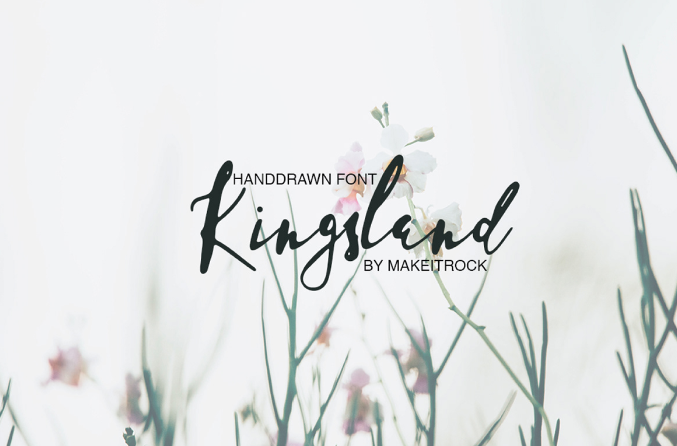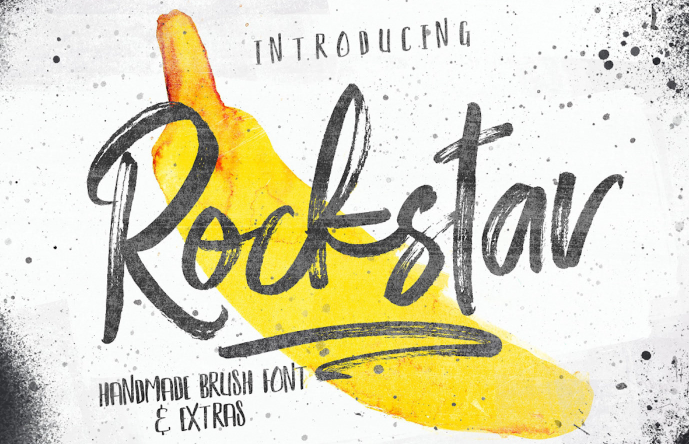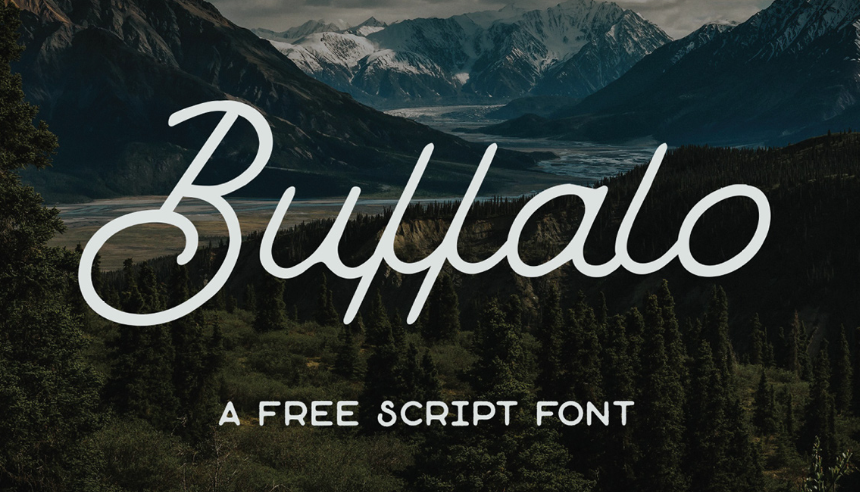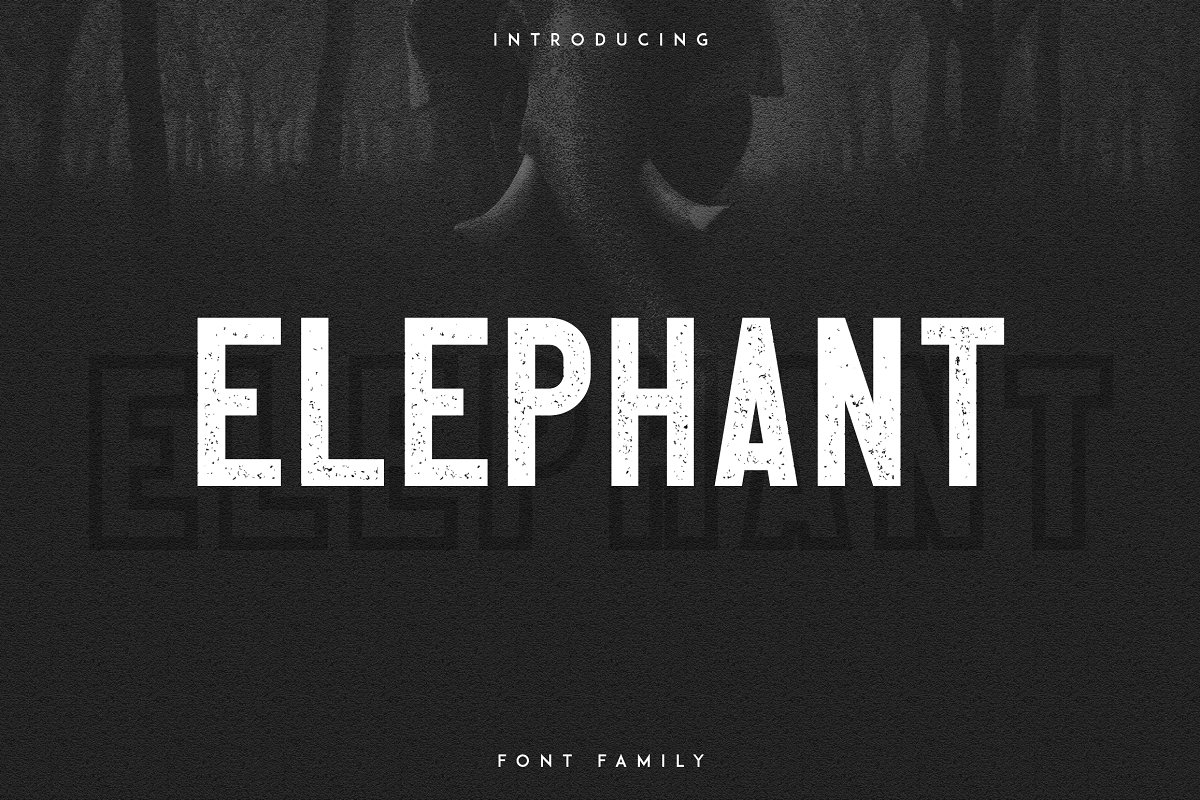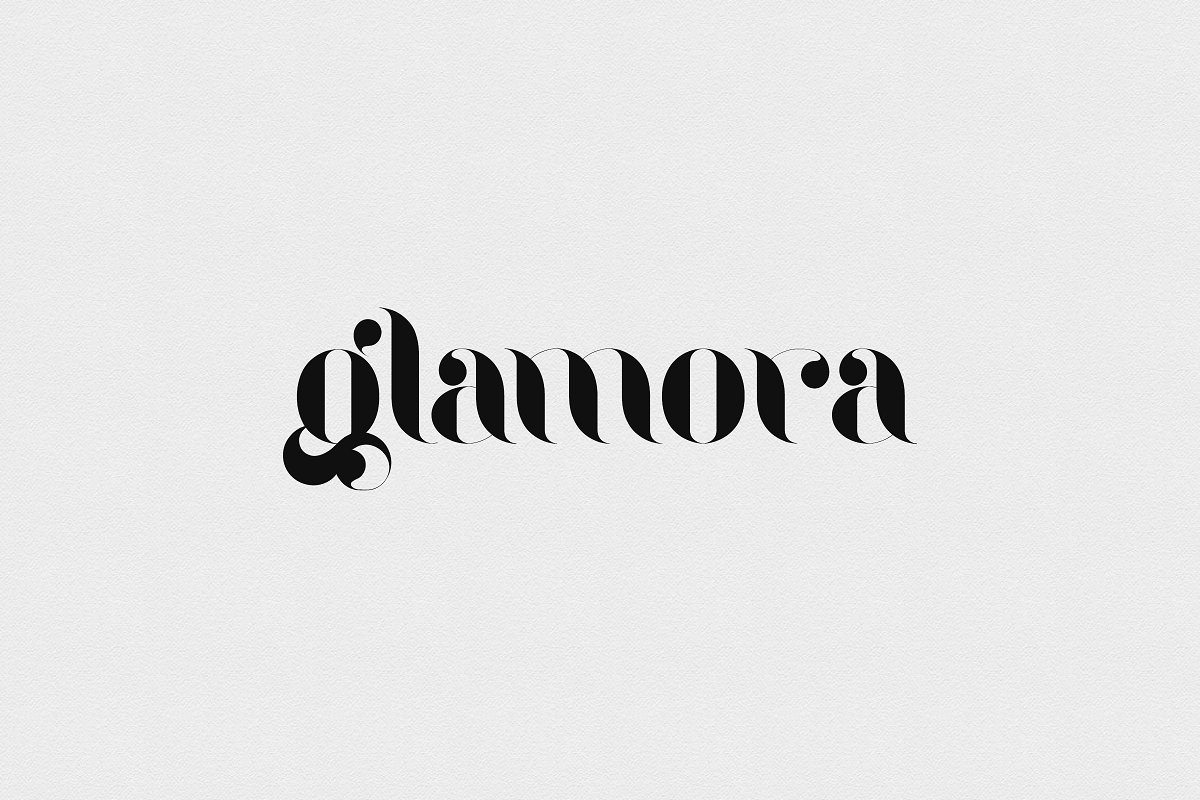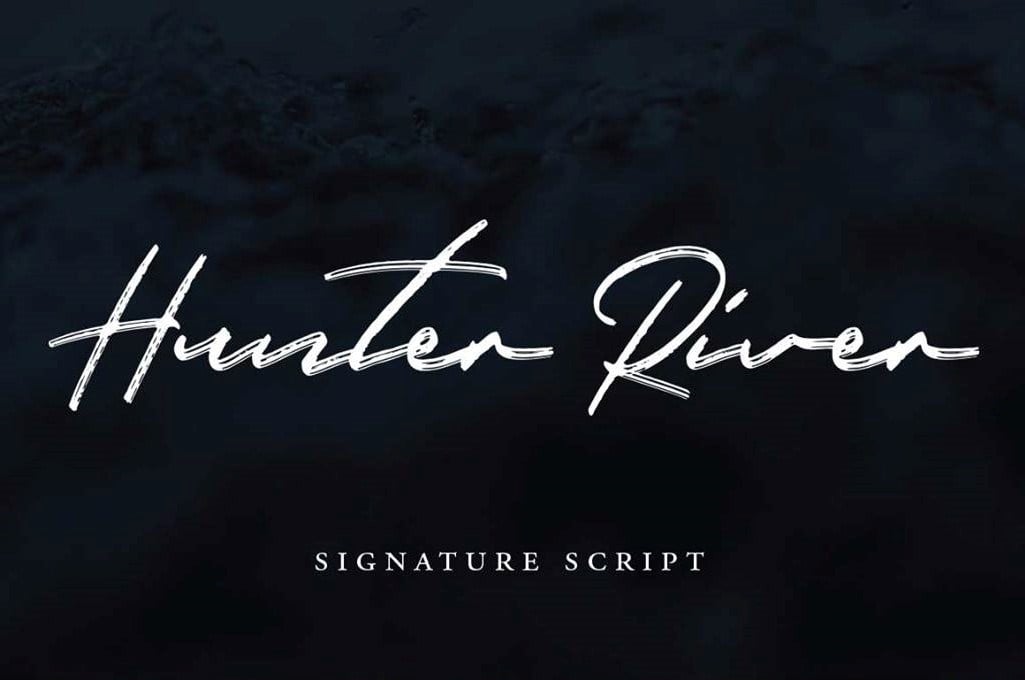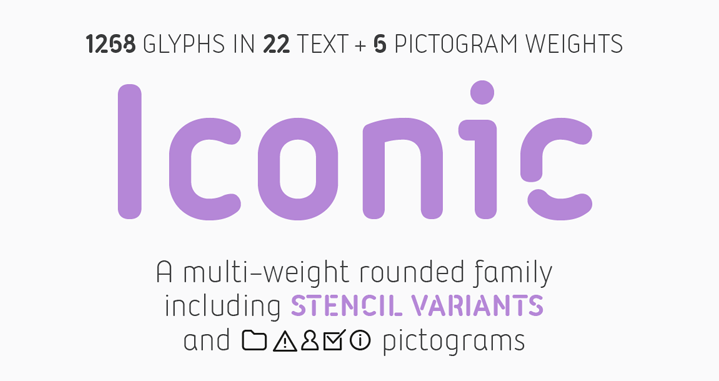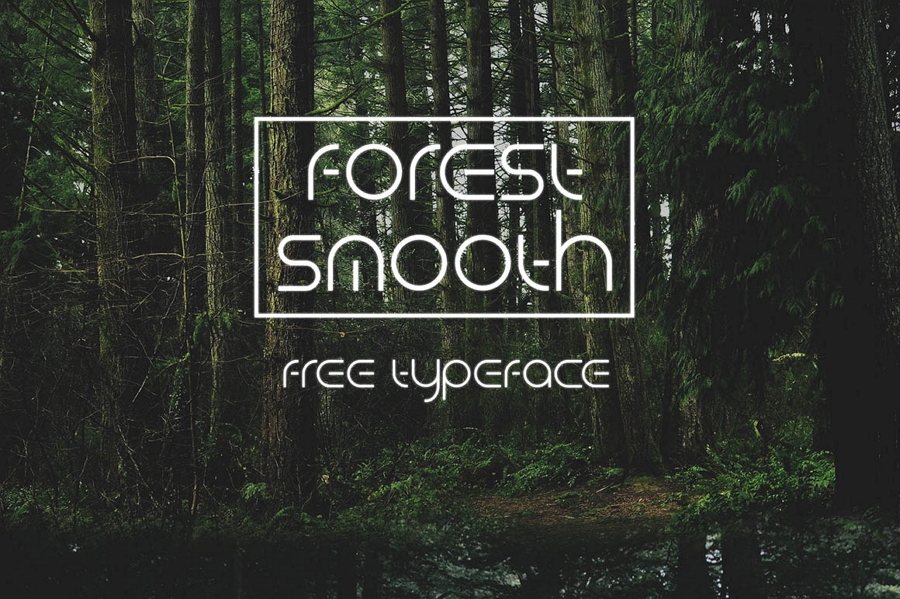
Elegir tipografías para diseñar logos suelen ser todo un reto. Seguro has pasado horas y horas entre diferentes páginas de tipografías, preguntándote cuál es la ideal para tu empresa y por eso nos hemos dado a la tarea de seleccionar 51 fuentes de logo memorables.
¿Cómo elegir la mejor fuente para tu logo?
A fin de seleccionar el tipo de letra adecuado, primero debes regirte bajo las reglas de la tipografía de un buen logo, las cuales son:
- Que esté alineada a la identidad corporativa: la fuente que elijas debe reflejar la personalidad y estilo de tu marca, para así mantener la coherencia en la comunicación y fortalecer tu posicionamiento en el mercado.
- Que sea legible: evita usar fuentes demasiado complejas que dificulten una lectura rápida de tu logo. Debe ser fácilmente comprensible sin importar si aparece en un cartel de vía pública o en una tarjeta de presentación.
Tip: una vez que hayas escogido tu fuente, asegúrate de mantener un espaciado adecuado entre las letras, ya que esto también facilitará la lectura.
No tienes por qué limitarte a utilizar solo un tipo de fuente en tu logotipo, aunque te recomendamos que no uses más de dos tipografías porque, de lo contrario, el mensaje perdería impacto. Si optas por emplear más de una fuente, asegúrate de que los estilos que selecciones se complementen y que haya una jerarquía. Evita utilizar tipografías parecidas entre sí para que las diferentes ideas se comuniquen de manera más clara.
En nuestra lista de tipografías para logos encontrarás fuentes modernas, creativas, elegantes y vintage para que puedas escoger la que más se ajuste a tus necesidades. Algunas son gratuitas, y otras son de uso comercial, por lo que te cobran una determinada cantidad, pero te permiten probar la versión de uso personal (te diremos dónde puedes adquirir la licencia comercial).
Las mejores tipografías para logos
- Modeka
- Nordic
- Ailerons
- Thinoo
- Baron
- Iconic
- Old Growth
- Braxton
- Doctor Glitched
- Forest Smooth
- Elephant
- Suprema
- Rockstar
- Moonglade
- Fixer
- I shot the Serif
- Kingsland
- Reckless
- Beaver
- Maxwell
- Hipstelvetica
- Lombok
- One Day
- Kolikö
- Olivia
- Black Pink
- Little Mandy
- Sugar Candy
- Hunter River
- Quando
- Glamora
- Aurellia
- Austral
- Poiret one
- Andis
- Coves
- Halo Handletter
- Coco
- Balqis
- Barista Script
- Smoothie Shoppe
- Buffalo
- Fibre
- Pixer
- ColorTube
- Perfograma
- Metropolis
- Aqua
- Cubic
- Sudoku
- Lovelo
Tipografías modernas para logos
1. Modeka - tipografía gratuita
Es una fuente legible, moderna y versátil; sus esquinas redondeadas le otorgarán un estilo elegante a tu logotipo. Pertenece a la familia tipográfica de las serif o romanas, por lo que te recomendamos utilizarla para la redacción de textos publicitarios o eslóganes.
2. Nordic - tipografía gratuita
Este tipo de fuentes, perteneciente a la familia tipográfica decorativa o de exhibición, está en tendencia. Nordic está inspirada en las runas noruegas y la puedes descargar en sus dos versiones: Regular y Alternativa, cada una con tres densidades distintas.
Te recomendamos utilizar esta fuente si buscas generar un impacto en tus clientes, porque es poco convencional. Si decides usarla en un spot publicitario, es preferible que escribas el nombre de tu marca con ella y el texto del anuncio con otra tipografía más legible; por ejemplo, alguna de la familia serif o sans serif, pero debes buscar que conserve las mismas proporciones y la similitud en formas.
3. Ailerons
Es una fuente inspirada en la industria aeronáutica, vanguardista e ideal para dar a tu logo un toque limpio y estilizado. Brinda una sensación de regularidad y legibilidad. Tiene 8 densidades y puedes utilizarla en cursivas (itálicas) o en su versión regular.
Aunque puede parecer una tipografía muy sencilla, justo su simplicidad te permite realizar dinámicas o juegos con colores y tamaños de fuente sin que se vea muy cargada la publicidad.
Contacta a su creador para usos comerciales.
4. Thinoo - tipografía gratuita
Esta fuente sans serif brindará sencillez y dinamismo a tu logo. Tienes a tu disposición mayúsculas, minúsculas, símbolos básicos y de puntuación. Además cuenta con dos pesos o densidades (light y bold).
Es una de las alternativas que puedes utilizar en combinación con otras tipografías, como Nordic. También puede venirle bastante bien a una campaña que requiera una tipografía uniforme para el logotipo y el texto de la publicidad.
5. Baron - tipografía gratuita
Baron está inspirada en los clásicos diseños de sans serif. Es elegante y puedes descargarla en su versión Upper/Lowercase y sus diferentes alternativas. Aunque no hay mucha diferencia entre mayúsculas y minúsculas, sus alternativas te ofrecen opciones más personalizadas y llamativas. Puedes utilizar estas versiones para el logotipo o marca de la empresa y la versión normal para el texto con más contenido.
6. Iconic
Descarga esta fuente sans serif redondeada, agradable y minimalista. Tal como la describen sus creadores, Iconic rememora la tecnología contemporánea. Si tu empresa está enfocada en la tecnología o medios digitales, será perfecta para tu logo.
Esta tipografía además te ofrece algo que muy pocas fuentes tienen: pictogramas. Si el estilo cuadra con lo que está buscando tu empresa, no dudes en utilizarla y explotar los elementos que la distinguen al máximo. También considera que su legibilidad la hace perfecta para la redacción de textos publicitarios, ya sean breves o extensos.
Consigue la versión completa aquí.
7. Old Growth - tipografía gratuita
Esta fuente es una sans serif inspirada en los bosques de la Costa Oeste americana: es moderna, pero sin perder toques rústicos. Es una fuente totalmente legible gracias a sus bordes anchos.
Las variantes que ofrece en algunas de las letras le dan mayor dinamismo, a la vez que conservan la sencillez que facilita la lectura. Cuenta con signos básicos, de puntuación y números. Considera esta tipografía si quieres un estilo elemental pero distintivo.
8. Braxton - tipografía gratuita
Esta fuente cursiva está inspirada en las grandes montañas del Reino Unido y la República Irlandesa. Es sofisticada y estilizada, por lo que un logotipo con esta tipografía lucirá selecto y original.
Forma parte de las tipografías script, rotuladas o caligráficas. Es una buena alternativa para tu logo, sobre todo si lo que buscas es generar un contraste con una segunda tipografía más sobria para el texto largo.
La estética de las fuentes glitch ha llegado para marcar tendencia. Doctor Glitch es una fuente distorsionada que evoca la interrupción o falla en el sistema, y es ideal para temáticas digitales e informáticas.
Detona estados de lucidez y energía, y es una buena alternativa para tu logotipo, pero no para textos. Pese a sus líneas rectas, no cuenta con vocales tildadas y tiene muy pocos signos de puntuación disponibles. Pertenece la familia decorativa o de exhibición y se codea con las sans serif, sin dejar de lado su carácter único.
Para adquirir una licencia comercial, haz clic aquí.
10. Forest Smooth
Es una fuente futurista, delgada y pulcra que transmite inteligencia y experiencia. Su diseño da una imagen amigable, por eso es perfecta para un logo que quiera demostrar personalidad.
Esta tipografía hará único el logotipo de tu marca. Solo considera que tiende a ir hacia la familia de fuentes de decoración o exhibición, por lo que su legibilidad en textos largos no es la mejor.
Aquí puedes adquirir la versión comercial.
11. Elephant - tipografía gratuita para uso personal
Elephant es una fuente bold y poderosa. Puedes descargar su versión completa y multilingual. Sin duda, le dará la actitud que tu logotipo necesita.
Forma parte de la familia sans serif, por lo que tienes garantizada la claridad y facilidad de lectura. Te permite seleccionar entre el contorno o la fuente bold. Aprovecha y crea una dinámica entre estas dos características, si quieres utilizar una misma tipografía con ligeros cambios.
Visita su versión comercial.
12. Suprema
Es una fuente tan sencilla que te encantará. Su diseño geométrico otorga elegancia, sin perder versatilidad. Por eso es ideal para diferentes tipos de industrias. Dada su legibilidad también puedes elegirla para la redacción de spots publicitarios.
La licencia comercial está en este enlace.
13. Rockstar - tipografía gratuita
Las tipografías de diseño «hecho a mano» son obligatorias en el catálogo de fuentes de cualquier diseñador. Rockstar transmite frescura y cercanía, que son cualidades con las que lograrás un logo muy creativo, divertido y casual.
Esta fuente pertenece a la familia tipográfica de las script o rotuladas y puedes aprovecharla si tu marca o empresa quiere dirigirse a un público juvenil, sobre todo en combinación con una tipografía más sobria para el texto.
14. Moonglade
Es una tipografía moderna y sofisticada que está inspirada en la Luna. Puede lucir simple, pero con su brillo y originalidad le darás a tu logo ese toque de profesionalidad y sobriedad que deseas transmitir.
Tiene líneas rectas que la hacen formar parte de la familia sans serif, por lo que la comprensión de tu logotipo y los textos que lo acompañen se hará sin dificultad. Cuenta con vocales tildadas y una variedad de símbolos. Además, ofrece dos estilos que tienden más hacia las formas redondas o rectas.
Conoce su uso comercial aquí.
15. Fixer - tipografía gratuita
Mira esta fuente bold con una imagen moderna e ideal para todo tipo de diseños. A pesar de que tiene rasgos duros, su diseño es único y original, y se hace divertido a la vista. Es atractiva y con mucha personalidad.
Debido a que cuenta con muchas densidades, que varían en estilo, puedes considerar utilizar esta tipografía para crear un efecto de mayor dinamismo.
16. I Shot the Serif - tipografía gratuita
¿Te encantó su nombre? Te gustará aún más su capacidad para transmitir un mensaje contemporáneo. Utiliza esta fuente si quieres decir: «este negocio se dedica a un sector conocido, pero hace las cosas de un modo diferente».
17. Kingsland - tipografía gratuita
Una fuente que procede de una escritura a mano, un tanto imperfecta, pero llena de originalidad y clase. Es legible y amigable, te hace sentir familiarizado y acogido por su natural diseño.
18. Reckless
Puedes elegir esta tipografía si deseas que tu marca dé una sensación de cercanía y calidez a la audiencia adecuada. Por su estilo relajado, es ideal si tu público meta es joven y lo que quieres es crear una conexión con él.
Tienes a tu disposición: mayúsculas, numerales, símbolos básicos y especiales. Es una alternativa que puedes combinar con otras fuentes de la misma familia script, como Kingsland. Para su uso con fines comerciales puedes entrar aquí.
19. Beaver - tipografía gratuita
Esta fuente sans serif de Goob Design Studio tiene un carácter con tendencia futurista. Si tu empresa ofrece soluciones enfocadas en el campo de la tecnología es una buena alternativa para tu logotipo.
Puedes utilizar mayúsculas, minúsculas, números y algunos signos especiales. Aunque posee algunos rasgos que no la hacen tan legible, puedes utilizarla para escribir un mensaje si tu empresa quiere destacarse en el ámbito creativo.
20. Maxwell - tipografía gratuita
Esta tipografía sans serif de Doublezero es muy legible. A pesar de esta claridad no pierde su distinción. Tiene tres densidades por lo que puedes jugar con ellas y utilizar la tipografía no solo para tu logotipo, sino también para escribir tu eslogan y mantener una uniformidad gráfica.
Otro motivo por el que puedes considerar usar esta fuente para eslóganes es que tienes a tu disposición símbolos básicos y especiales. Por ello no representará un problema escribir y probar distintas dinámicas en tu estrategia y creación de textos breves con ella.
21. Hipstelvetica - tipografía gratuita
Es una fuente basada en la clásica tipografía Helvetica. Por sus características la recomendamos para logos de una marca o producto cuya identidad exija algo fuera de lo común.
Esta fuente solo cuenta con letras mayúsculas, números y símbolos básicos. Si complementas su uso con otra fuente de la familia sans serif puedes crear una combinación interesante. Puedes descargarla directamente del sitio del autor.
22. Lombok
Una fuente muy angular y geométrica con formas divididas que hace lucir cualquier texto. Se trata de un tipo de letra serif con curvas refinadas. Sin duda un logo con esta tipografía será llamativo y se distinguirá frente a otros.
23. One Day - tipografía gratuita
Estamos ante una fuente estilizada, con formas redondeadas y líneas quebradas que le dan fuerza a un texto. Imagina tu logo con esta tipografía de interesantes diseños, con la que ganarás en identidad y distinción. Además se adapta muy bien a fondos o textos sobre imagen.
Es una tipografía sans serif, ligera y con personalidad, pero solamente la puedes usar en mayúsculas.
24. Kolikö - tipografía gratuita
Contiene caracteres latinos y cirílicos en estilo regular, delgado y negrita. Se trata de una tipografía geométrica sans serif con una estructura limpia para encabezados vistosos y que busquen dar una sensación de innovación y vanguardia.
Tipografías elegantes para logos
25. Olivia - tipografía gratuita
Si tienes gusto por las fuentes caligráficas, entonces Olivia se convertirá en tu favorita. Sus curvaturas le dan clase y romanticismo. Utilízala si deseas que tu logo tenga una imagen sofisticada.
Es ideal si lo que estás buscando es firmar un spot publicitario con el nombre de tu marca. Su estilo manuscrito transmite la sensación de una firma real. Por este motivo, puedes considerar emplear otra tipografía sans serif para redactar mensajes y que contraste con esta.
Aquí puedes comprar su licencia.
26. Black Pink
Aprecia esta caligrafía ideal para otorgar lujo y delicadeza a tu logotipo. Su diseño es estético y suave, pues sus líneas delgadas le proporcionan la ligereza que la hace tan especial.
Como en el caso anterior, puedes utilizarla para crear un logotipo de firma. De igual modo, puedes considerarla para campañas muy concretas, como las navideñas, que buscan generar una sensación de calidez en los lectores.
Adquiere su licencia de uso comercial en este enlace.
27. Little Mandy
Seguro esta fuente te parece conocida y tienes razón, pues varias publicaciones la han usado. Además de ser elegante, tiene una apariencia amigable. Cuenta con mayúsculas, minúsculas, números y símbolos.
Esta fuente script tiene una ventaja adicional en comparación con las dos tipografías anteriores: cuenta con elementos que personalizan el enlace entre las letras. Es tu alternativa si quieres generar un mensaje original.
Consigue la licencia comercial en este sitio.
28. Sugar Candy
Su diseño limpio está inspirado en una clásica tipografía cursiva, pero con líneas más gruesas. Es perfecta para evocar naturalidad y sutileza.
Cuenta con dos alternativas para letras mayúsculas y minúsculas. Tienes a disposición también números y símbolos básicos en caso de que quieras escribir textos con más contenido.
Adquiere aquí la licencia comercial.
29. Hunter River - tipografía gratuita
Es una fuente script con un estilizado diseño que es serio y discreto, a la vez que sofisticado. Es ideal para quienes buscan logos sencillos, lineales y con una imagen elegante.
Se presta mucho para crear logos con un aire de firma. Además cada letra da la sensación de haber sido escrita a mano por los detalles y ligereza. Puedes diseñar tarjetas de presentación o spots combinándola una fuente sans serif.
30. Quando - tipografía gratuita
Puede lucir como una fuente sencilla, pero es precisamente ese detalle el que la hace tan sofisticada. Es ideal para logos de diferentes sectores. Es legible y con espacios entre palabras perfectos que puedes aprovechar para frases sencillas. Al ser una fuente de la familia serif, sus detalles y redondeces la hacen ideal para quienes quieren obtener un estilo elegante y delicado a la vez.
Forma parte del catálogo de Google Fonts por lo que su licencia es abierta y gratuita.
31. Glamora - tipografía gratuita
Tal como su nombre lo dice, es una fuente glamorosa que transmite lujo y exclusividad. Puede funcionar para un logotipo de la industria de la moda.
Aunque forma parte de la familia tipográfica serif, sus curvas la acercan también a las fuentes de la familia script. Te ofrece dos alternativas: Regular y Stencil. Debido a que solo cuenta con mayúsculas y minúsculas, te sugerimos que la uses de preferencia para el logotipo.
La ventaja que tiene al pertenecer a la familia serif es que no te costará tanto trabajo seleccionar una fuente complementaria, si quieres brindar una sensación de uniformidad en tus mensajes publicitarios.
32. Aurellia
Aurellia otorga lujo con su caligrafía. Se caracteriza por sus ligaduras delgadas y suaves que la hacen lucir con finura. Es perfecta si deseas que tu logo transmita un toque clásico y tradicional.
Como otras fuentes de la familia script que te hemos presentado, puedes combinarla con una fuente de las familias serif o sans serif, dependiendo de la uniformidad o contraste que quieras generar en tus contenidos.
Consigue su licencia para el uso comercial.
33. Austral - tipografía gratuita
Las fuentes caligráficas nunca pasan de moda. Esta es una tipografía muy juvenil que encaja en diferentes tipos de proyectos. Sus ligaduras anchas permiten una lectura fácil, por lo que no te preocuparás de que el nombre de tu marca no se entienda.
Esta tipografía de la familia script ofrece la posibilidad de personalizar el enlace de letras para crear estilos únicos, pero solo lo lograrás en programas como PopChar. Una de las ventajas que esta tipografía presenta es que su desarrollador ofrece su correo para resolver las dudas que puedan surgir respecto a este u otros aspectos.
34. Poiret One - tipografía gratuita
Si buscas una tipografía elegante y sencilla, Poiret One es para ti. Esta basada en formas geométricas y tiene una dinámica activa entre las líneas y las curvas. Aunque no cuenta con un extenso catálogo de símbolos, sí ofrece la posibilidad de escritura alfanumérica y cirílica.
La claridad y sobriedad que transmite esta fuente puede darle el toque profesional que necesita el logotipo de tu marca. Forma parte del catálogo de Google Fonts y también puedes considerar utilizarla en combinación con alguna tipografía decorativa, ya que esta tiene más claridad y consistencia. Por sus líneas rectas y elaboración geométrica incluso se acerca a la familia de las sans serif.
35. Andis
Esta tipografía sans serif es sencilla, funcional y expresiva. Por ello representa una buena alternativa para un logotipo elegante, sin un estilo cargado. Te ofrece la posibilidad de seleccionar entre tres densidades o pesos y entre sus versiones regular e itálica.
También es una buena opción si lo que buscas es una fuente secundaria para escribir un texto. Su sencillez la hace ideal para contrastarla con fuentes de la familia decorativa e incluso con una de la familia script.
Da clic aquí para acceder a la licencia de uso comercial.
36. Coves
Esta tipografía, basada en la familia sans serif, apela por la uniformidad en los trazos con una tendencia a formas redondeadas. Sus rasgos le brindan elegancia y sobriedad.
Coves cuenta con mayúsculas, minúsculas y símbolos básicos. Además puedes elegir entre densidades, por lo que puedes aprovecharla para escribir el logotipo y debajo el eslogan. Para acceder al uso comercial visita este link del sitio del diseñador.
37. Halo Handletter - tipografía gratuita
Se trata de una fuente que mezcla sofisticación con un toque divertido. Las letras mayúsculas están inspiradas en trazos de pincel y son muy fáciles de leer. El reflejo de una escritura a mano en cursiva hace que cualquier texto se vea elegante, por lo que tu logo lucirá genial con una fuente de este estilo.
38. Coco - tipografía gratuita
Una fuente cuya inspiración es la marca Coco Chanel, por lo cual podrás adivinar que proyecta sutiliza y buen gusto. Las letras en negrita y altas pueden dar una vista potente a cualquier logo. Los textos que usan esta tipografía tienen que ver con el lujo, la moda y la elegancia, además se utiliza mucho para grandes titulares en portadas de revista.
39. Balqis - tipografía gratuita
Se trata de una tipografía con gran sutileza. Luce como si fuera una caligrafía delicada a rayas que presenta un sentimiento casual y natural. Destaca para textos que busquen un alto contraste. Sus líneas la hacen muy legible.
Tipografías vintage para logos
40. Barista Script - tipografía gratuita
Es una tipografía muy creativa, cuyos enlaces semejan cuerdas. Te da todos los elementos que necesitas para crear un gran logo. Puedes descargarla con sus características OpenType.
Como otras de las tipografías de la familia script, representa una gran opción para diseñar logotipos tipo firma. Además, te permite personalizarla para darle a tu logo un toque aún más original.
41. Smoothie Shoppe
Es una fuente grande y flexible con un toque encantador y divertido. Es brillante y con detalles que la hacen exquisita y apta para muchos logotipos. Una de sus singularidades es que te ofrece opciones para lettering y ornamentos para crear títulos, secciones y etiquetas.
Es una tipografía script con bastante uniformidad y legibilidad. Puede ser lo que estás buscando si quieres un equilibrio entre encanto y sobriedad.
Puedes obtener la licencia estándar haz clic aquí o explora la tienda de su diseñadora, sobre todo si lo que estás buscando son alternativas dentro de la familia tipográfica script.
42. Buffalo - tipografía gratuita
Una hermosa fuente en cursiva, perfecta para hacer ver tu logo con un toque vintage. Como la tipografía anterior, es muy legible y su anchura le da mayor realce al texto que desees incluir.
La puedes considerar en combinación con fuentes de la familia sans serif que tiendan hacia formas redondeadas, ya que no tiene un estilo muy cargado.
43. Fibre - tipografía gratuita
Por último en esta categoría, te presentamos esta fuente sans serif escrita a mano con un carácter vintage y sencillo. Cuenta con mayúsculas, números y símbolos básicos. Por la falta de más símbolos, quizá no sea muy útil para escribir un mensaje o un eslogan. Pero siempre puedes tomarla en cuenta para crear con ella el logotipo de tu marca.
Esta fuente es una buena alternativa si consideras que tu marca necesita un toque de cercanía, y piensas que una tipografía script no cuadra con el estilo. También viene bien utilizarla si tu empresa quiere darle un carácter retro y algo artesanal al logotipo.
Tipografías creativas para logos
44. Pixer- tipografía gratuita
Es una tipografía de la familia decorativa o de exhibición de FontFabric, que puede ser utilizada idealmente si el concepto de tu marca quiere apelar a la nostalgia que evoca su diseño. No querrás dejar de utilizarla si tu empresa o marca forman parte de la industria digital o del mundo de los videojuegos.
45. ColorTube - tipografía gratuita
Esta tipografía quizá no sea la más creativa, pero sí la más colorida. Es la fuente que estabas buscando si quieres crear un impacto a través del juego de colores.
Por la estructura de su diseño pertenece a la familia tipográfica sans serif, por lo que no tendrás que sacrificar la legibilidad y, a la vez, podrás seguir destacándote entre tu competencia.
Aunque ahora solo cuenta con los caracteres básicos para el alfabeto latino, símbolos monetarios básicos y números, su diseñador planea incorporar el alfabeto cirílico y vocales tildadas en un futuro. Es una fuente de código abierto con licencia creative commons, por lo que puedes usarla libremente.
46. Perfograma -tipografía gratuita
Esta fuente diseñada por Asen Petrov está inspirada en las tarjetas que utilizaban las primeras computadoras de IBM (Mark 1) y forma parte de la familia tipográfica decorativa o de exhibición.
Por sus líneas y estilo puede ir bien con una fuente de la familia sans serif. Es una fuente muy original que posee caracteres del alfabeto latino, cirílico, números y signos de puntuación básicos. La puedes descargar y utilizar para uso comercial sin ningún costo, pues su licencia es creative commons.
Si tu empresa se encarga de la tecnología y planea rescatar o narrar la historia de los ordenadores para tu marca personal, puedes utilizarla a fin de que haya una consistencia sólida en la identidad de marca.
47. Metropolis - tipografía gratuita
Es otra tipografía de la familia decorativa que, por su diseño de líneas rectas, puede combinar muy bien con fuentes sans serif. Otorga un estilo sobrio pero también sofisticado, y aunque solo cuenta con caracteres alfanuméricos, es una excelente opción si lo que estás buscando es crear un logotipo original, sencillo y elegante para tu marca.
La simplicidad en sus trazos y las reminiscencias geométricas en su diseño solucionan el problema de disponibilidad limitada de caracteres para la escritura, ya que con facilidad podrás encontrar una tipografía complementaria para tus spots y campañas.
48. Aqua - tipografía gratuita
Esta fuente diseñada por Laura Pon destaca por el contraste que crea entre sus formas circulares y sus líneas rectas. Puede estar en armonía con alguna tipografía de la familia sans serif o contrastar con una fuente más ornamentada.
Es sobria, artística y elegante. Sus elementos la hacen ideal para títulos en un póster publicitario.
49. Cubic
Es una fuente decorativa que le da prioridad a las formas lineales con tendencia a ángulos rectos. Tiene un catálogo muy amplio de caracteres y puede darle un toque futurístico y experimental a tu logo y a tus textos.
Te permite elegir tres estilos, entre los cuales hay una tipografía en 3 dimensiones. Para adquirir la licencia de cualquiera de los estilos, o un paquete con los 3, puedes ingresar a esta página.
50. Sudoku
Esta tipografía pertenece a la familia de exhibición o decorativa. Cuenta con 5 estilos diferentes para que elijas el que mejor vaya con la marca personal de tu producto. Sudoku es tu alternativa si buscas una fuente que juegue con líneas paralelas y círculos.
Para conocer más sobre la licencia de alguno de los estilos o para adquirir el paquete completo, entra aquí.
51. Lovelo - tipografía gratuita
Lovelo es ideal para ti si buscas una fuente que te permita navegar entre las familias tipográficas decorativas y sans serif. Cuenta con tres estilos diferentes (black, line-bold y light) y representa una gran alternativa por la prioridad que le da a las líneas rectas.
Si quieres crear un logotipo con uniformidad pero dinámico, puedes utilizar los estilos line y black para lograr ese efecto. También puedes optar por utilizarla en combinación con una fuente sans serif para escribir un mensaje o spot publicitario, con la certeza de que lograrás un equilibrio óptimo.
Crea una tipografía usando la guía de HubSpot e Illustrator
En nuestra guía sobre cómo crear tu propia tipografía encontrarás un tutorial paso a paso para crear una tipografía personalizada en Adobe Illustrator.
Ya sea para reflejar la personalidad de tu marca en una campaña de marketing o para hacer que tu pitch comercial destaque, una tipografía personalizada puede ayudarte a destacar visualmente.
Con esta guía paso a paso aprenderás los aspectos básicos de una tipografía y darás los primeros pasos para crear tus propias fuentes tipográficas en poco tiempo haciendo uso del software Adobe Illustrator.
¡Ya tienes la inspiración que necesitas! Esperamos que con nuestras recomendaciones puedas encaminar de mejor forma el diseño de tu logotipo.
Recuerda que no tienes que elegir un solo estilo de fuente, sino que puedes hacer combinaciones que se equilibren para llegar a tu objetivo. Si aún no sabes cómo lograrlo, puedes pedir apoyo a un diseñador para que te guíe en este proceso.